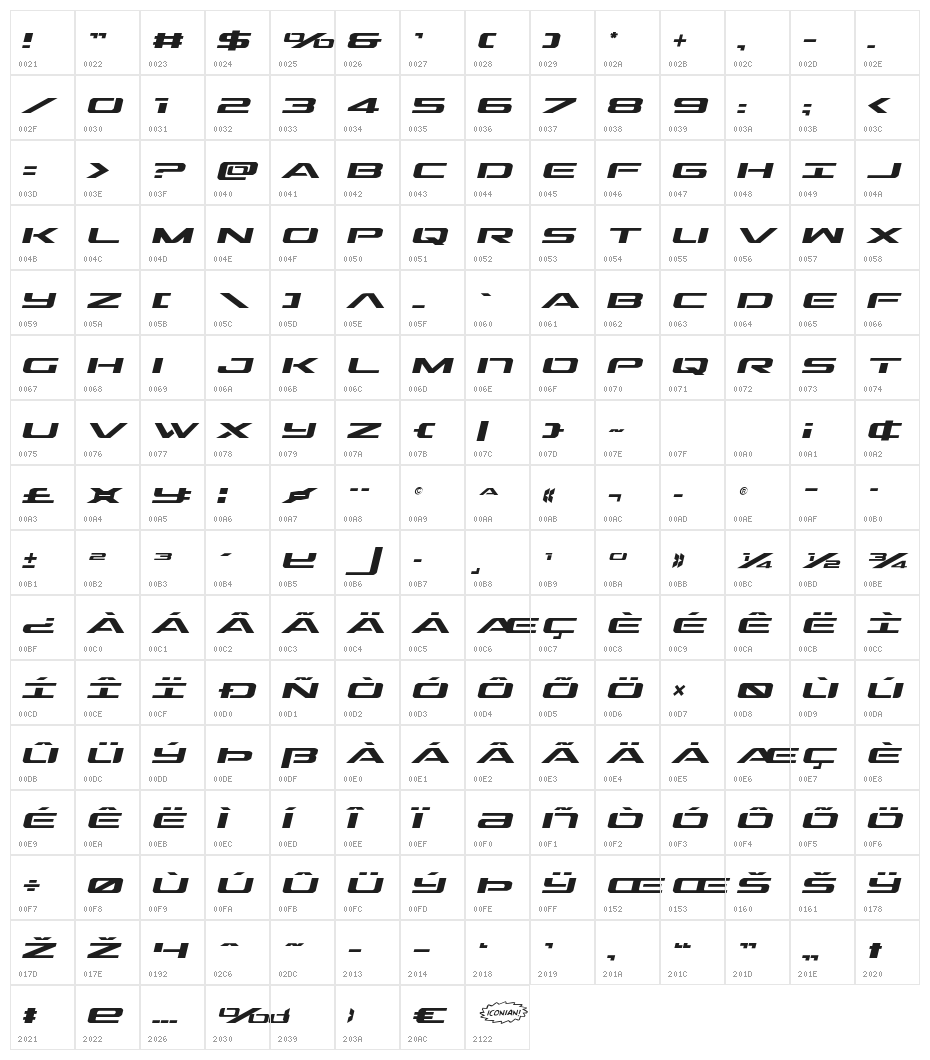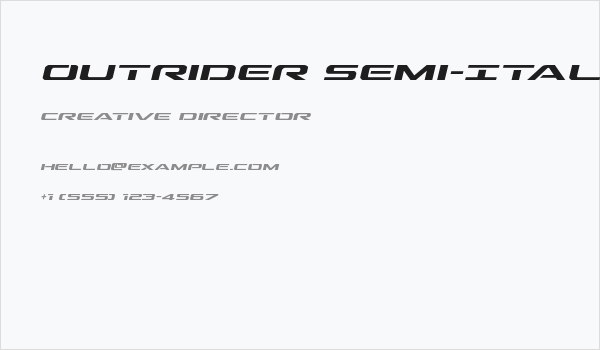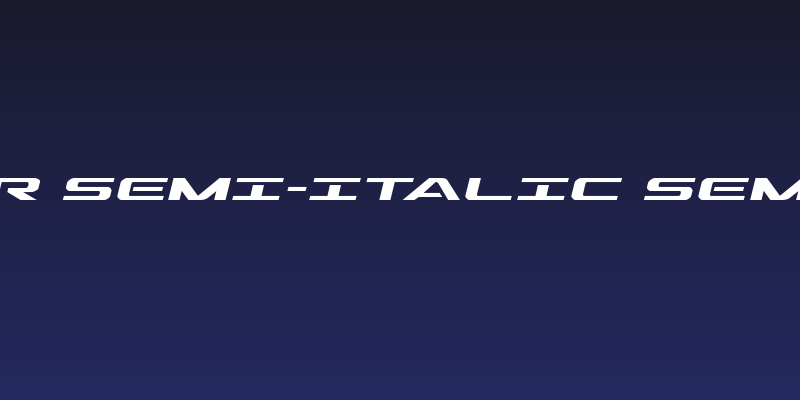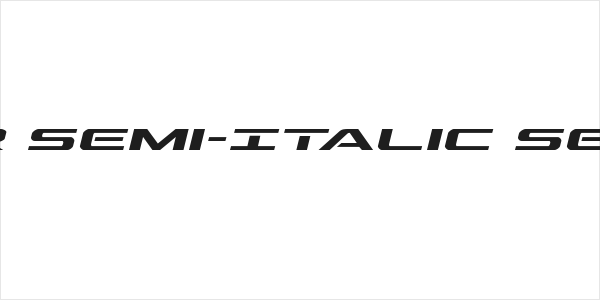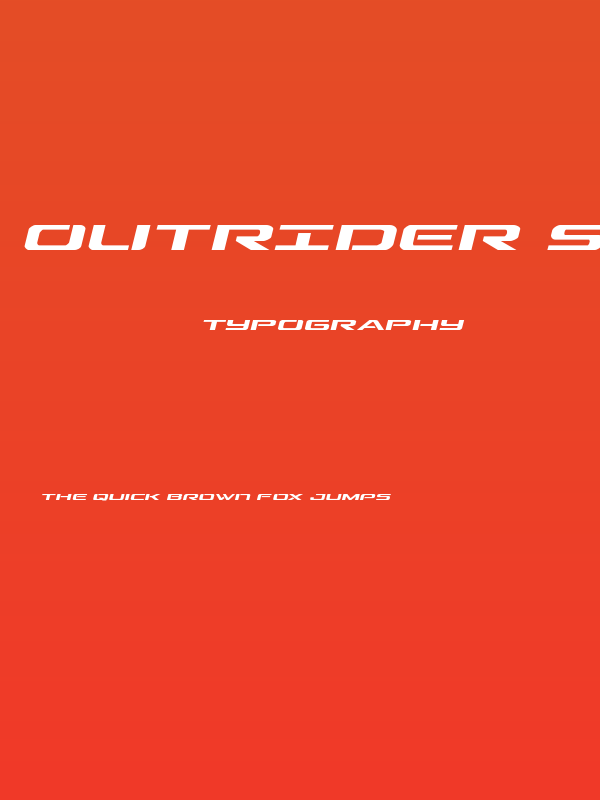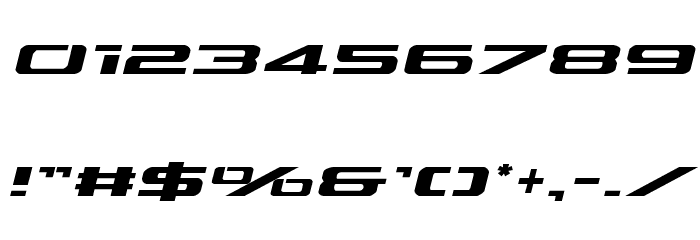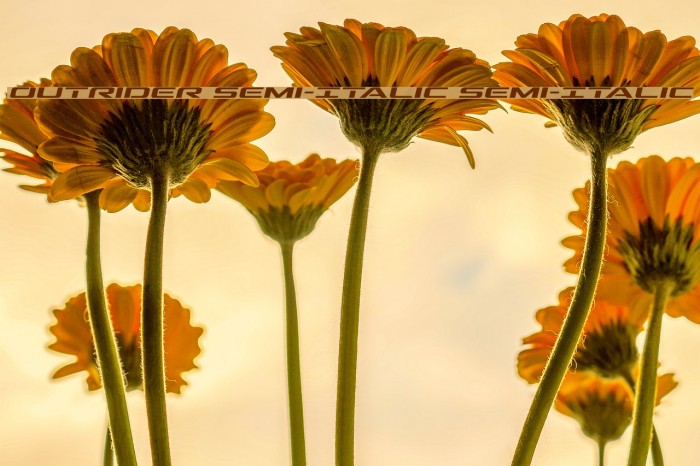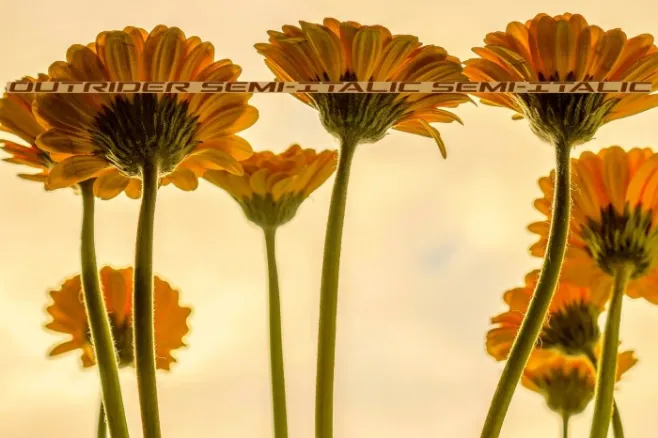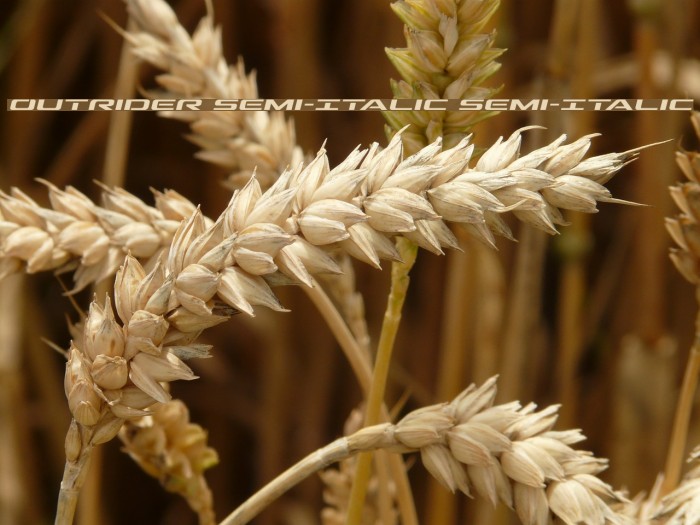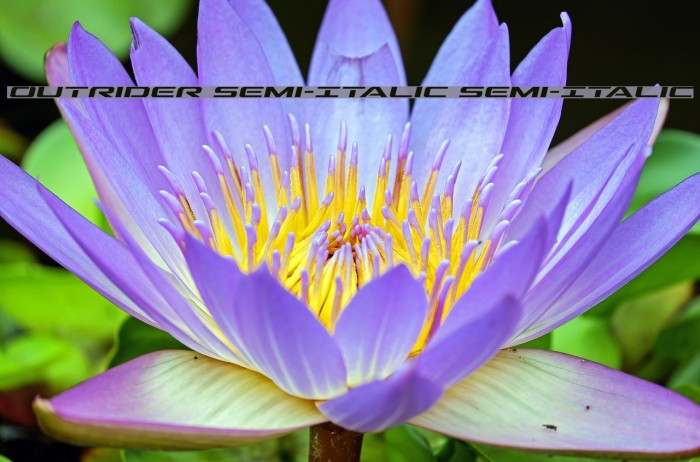
Outrider Semi-Italic Font
✎ Futuristic
| Anwendungsfall | Logos, Headlines, Branding |
| Vorgeschlagene Projekte | Ideal for branding, sports team logos, automotive designs, and tech-related projects. |